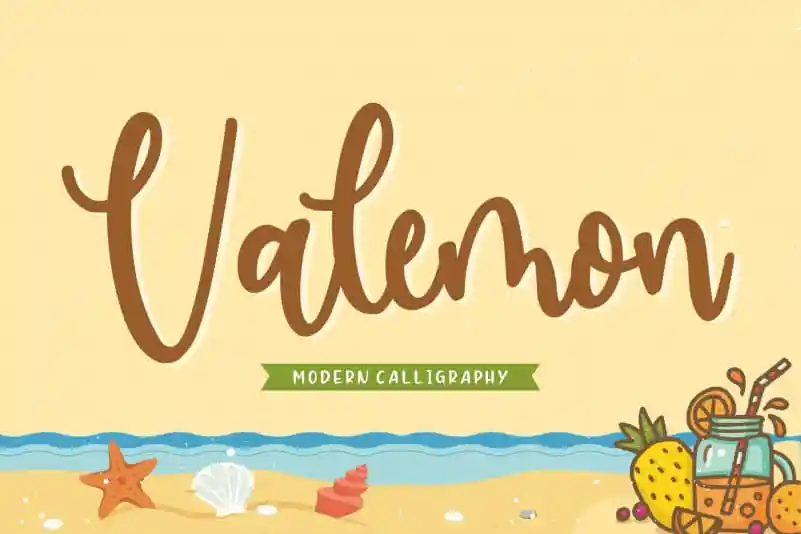
Valemon Modern Calligraphy Font
Valemon Modern Calligraphy Font é uma elegante escolha para qualquer projeto que valoriza detalhes e graça no design. Conhecida por sua harmonia perfeita entre modernidade e sofisticação, esta fonte moderna está idealmente adaptada para a criação de embalagens de produtos, identidades de marca e editoriais em megazines, bem como se destaca nos seus perfis nas redes sociais. Perfeitamente adequada para expressar frases importantes sobre um fundo, Valemon Modern Calligraphy é uma fonte perfeita para eventos especiais, como casamentos, ou até mesmo quando você deseja fazer uma assinatura única em sua página de background. O designer balpirick trouxe ao mundo uma opção versátil e incrivelmente atraente para aqueles que valorizam um toque único em seus trabalhos gráficos.